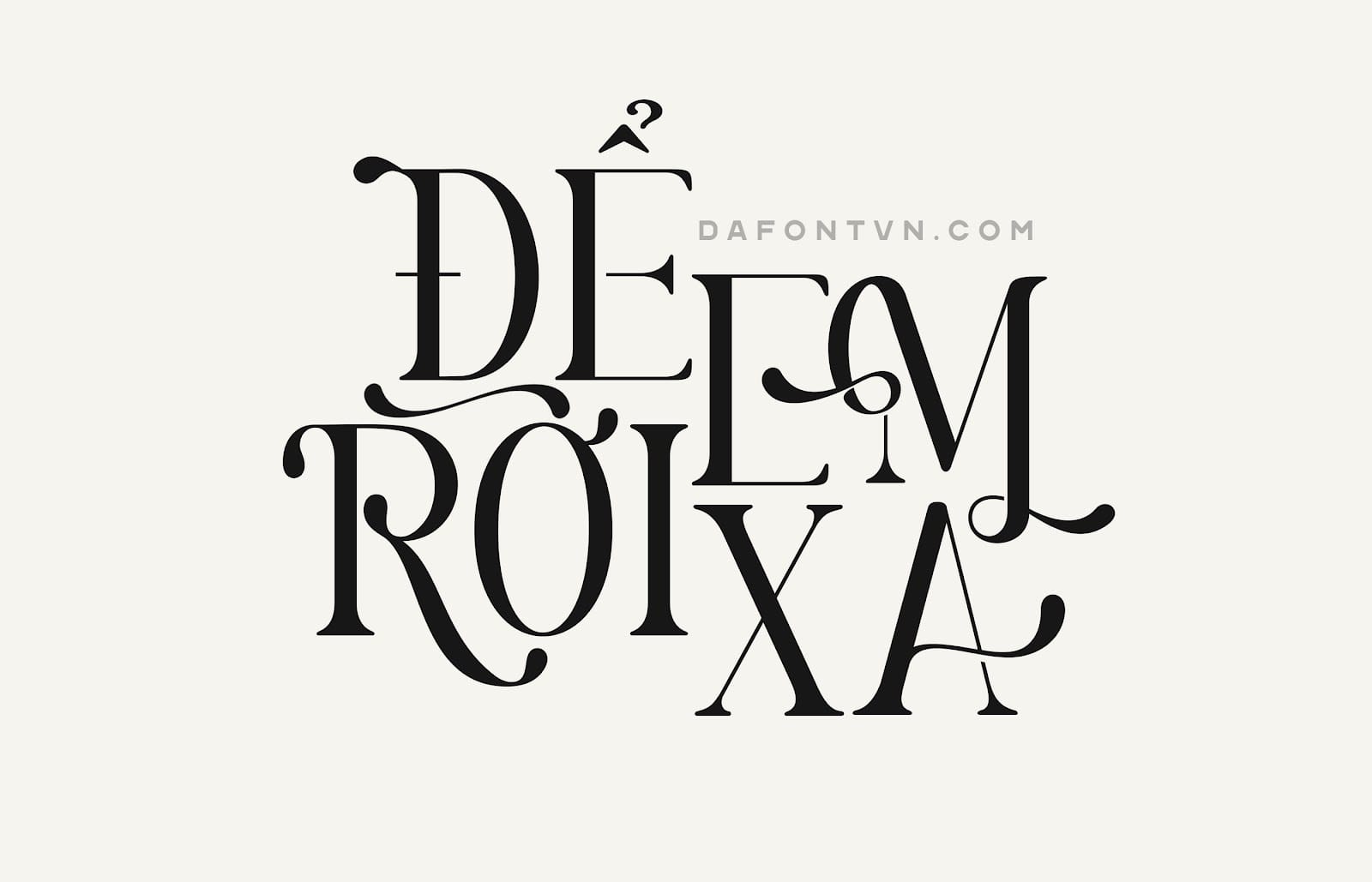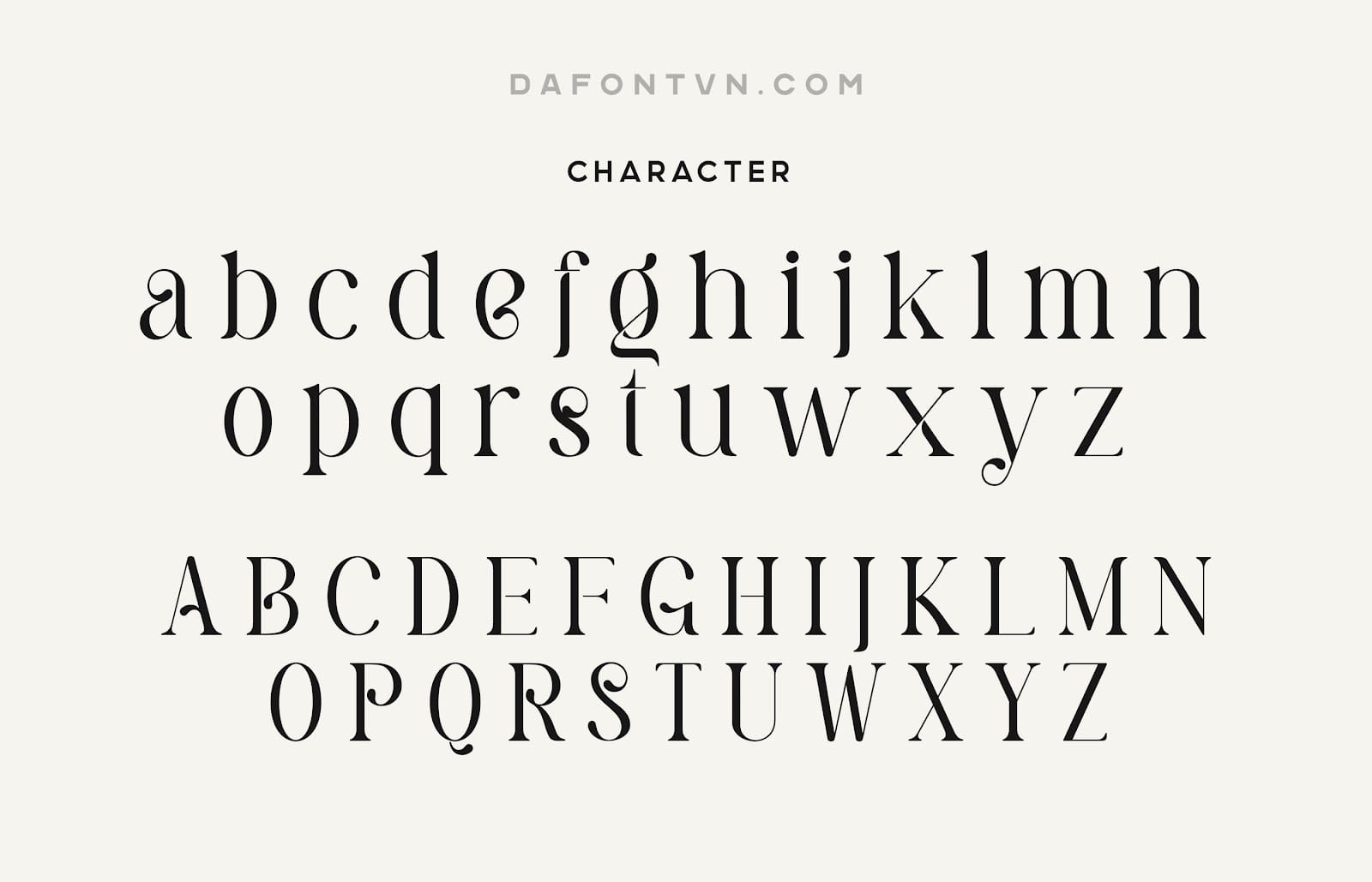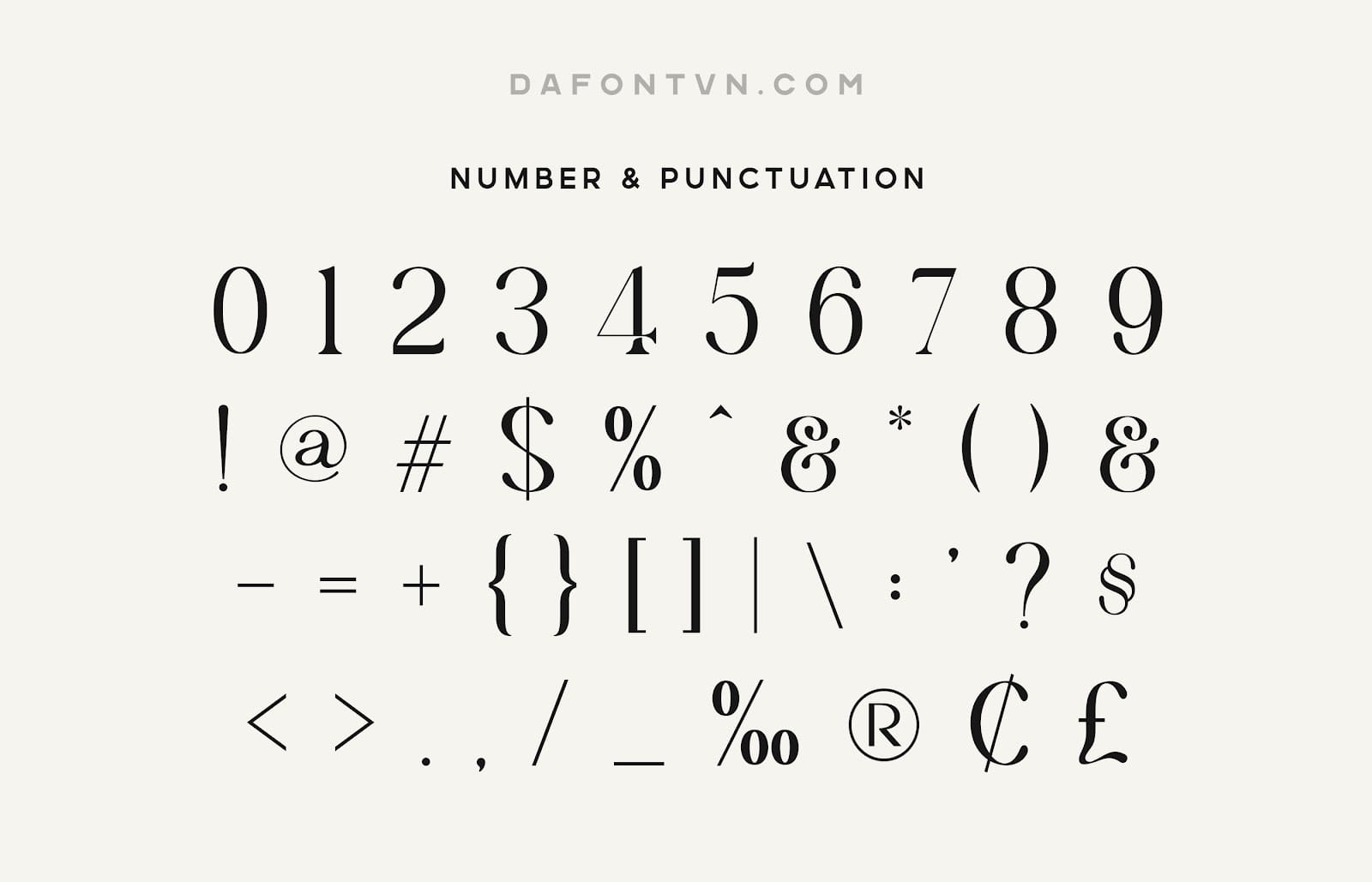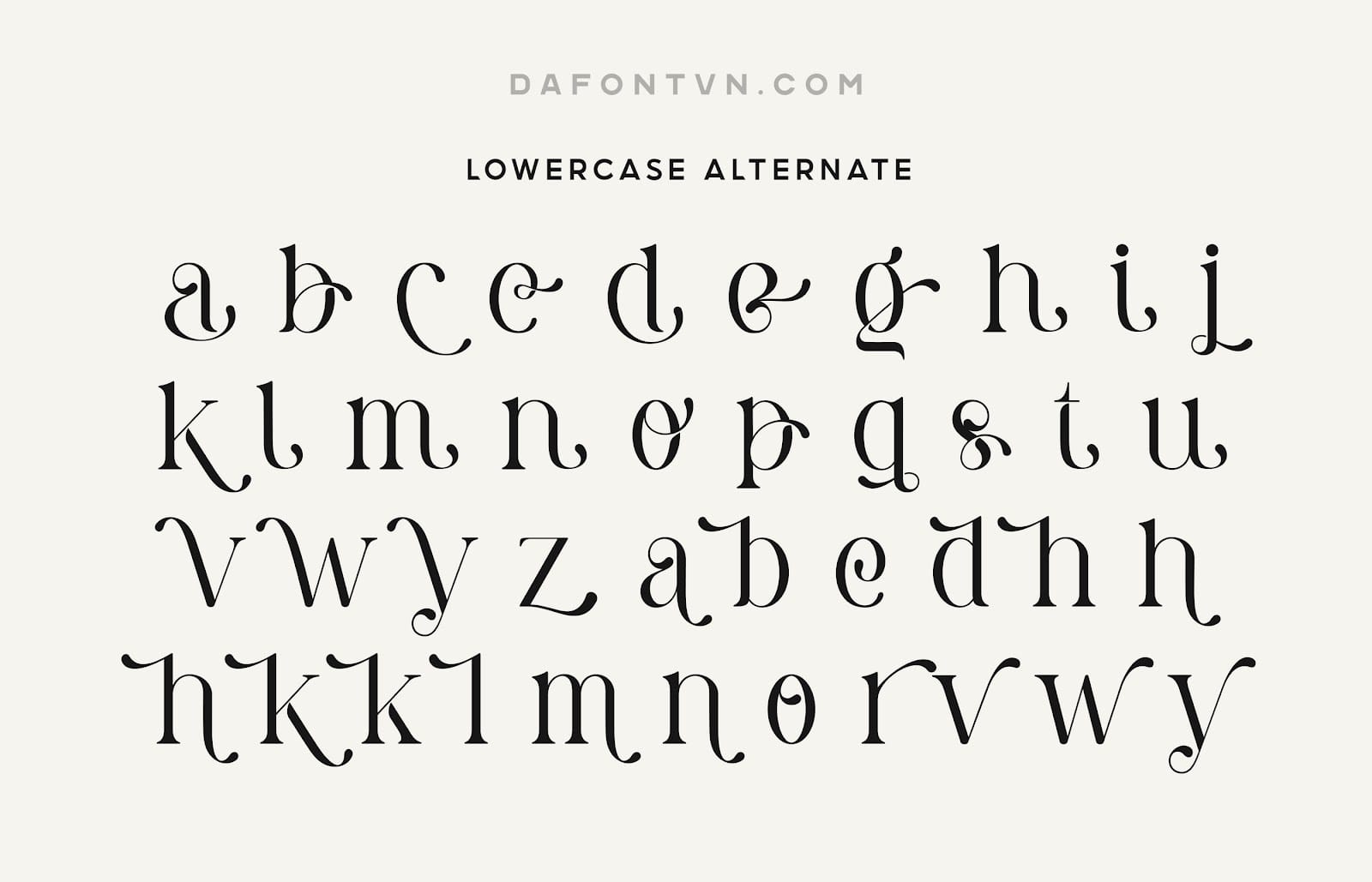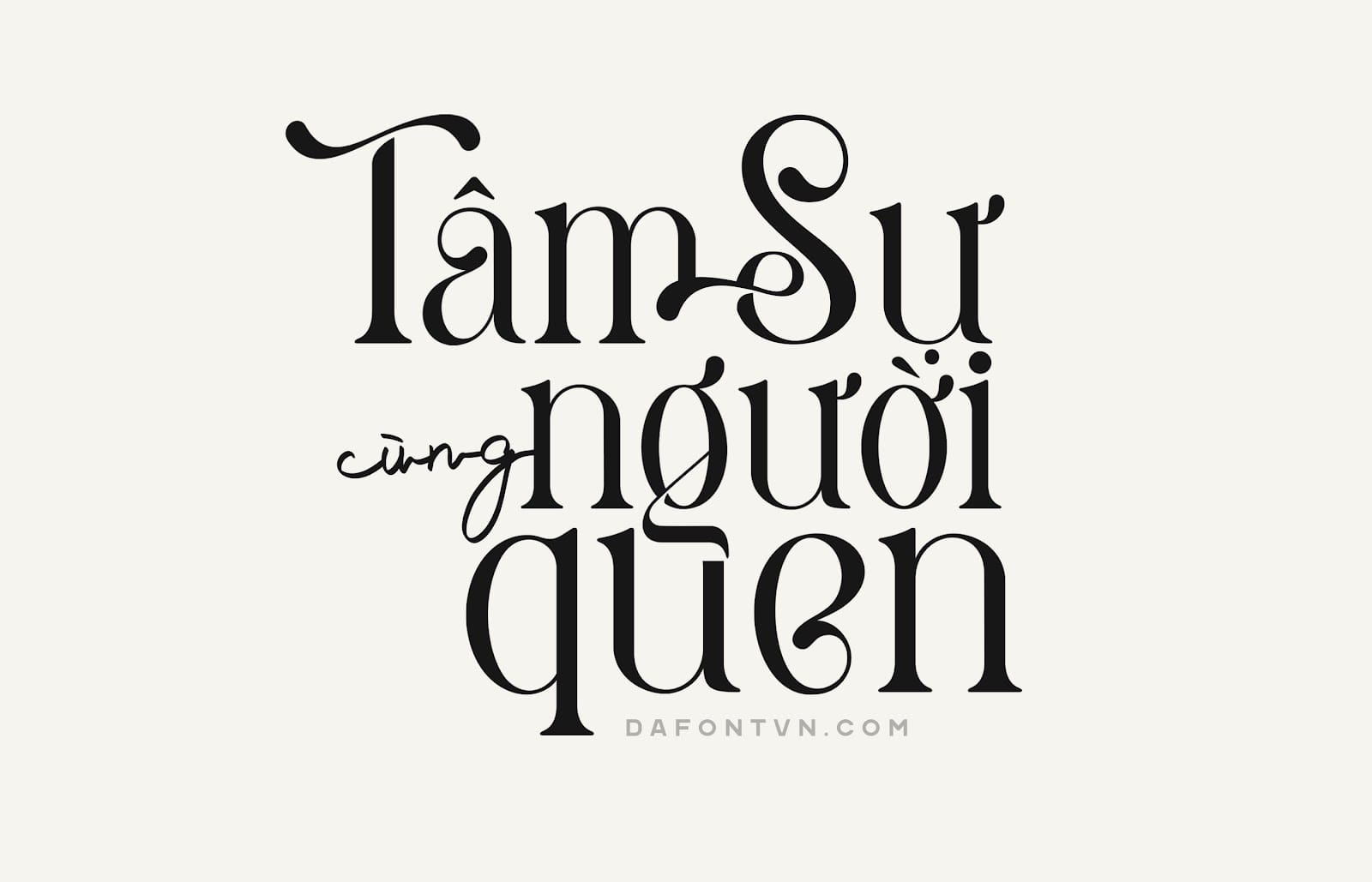
Pastel Orange là kiểu chữ serif giản dị và rất đẹp với các thiết kế đuôi tròn ấn tượng phù hợp cho rất nhiều các thiết kế khác nhau như thiết kế bao bì, tạp chí, typography, quotes hoặc bất kỳ thiết kế nào đòi hỏi 1 font chữ hiển thị tốt. Ngoài ra font chữ đi kèm với rất nhiều glyph đẹp bao gồm cả chữ hoa và chữ thường để bạn có thể tạo ra các thiết kế ấn tượng hơn.Font Pastel Orange việt hóa đầy đủ, kerning, chỉnh sửa và được mã hóa PUA để bạn có thể truy cập tất cả các glyph và swash một cách dễ dàng, cũng như có thể sử dụng trên bất kỳ phần mềm thiết kế nào.